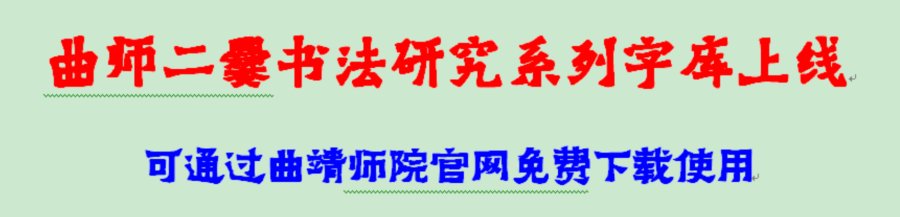
6月10日下午,由我校二爨书法研究所研发的“曲师大爨建国字库”上线,《爨体书法字库》首发,这是我校推进爨文化传承创新,继2017年“曲师二爨培生字库”上线之后,对“南碑瑰宝”爨龙颜碑和爨宝子碑进行数字化研发的又一重要成果。可通过曲靖师范学院官方网站下方快速链接免费下载“曲师二爨字库”,实现资源共享。
据悉,本次所推出的“曲师大爨建国字库”以“爨龙颜碑”为基础,在保持原碑风格特征的基础上,对原碑1239字(碑阳、碑阴)进行提炼和转化,以GB2312简体字库及GBK繁简字库为标准,对字形笔画的所有书写特点,造型元素反复揣摩,历经8万余字次的调整修正,推出“曲师大爨建国字库(简体)”“曲师大爨建国字库(繁简)”、“曲师大爨建国字库(繁体)”三个版本。《爨体书法字库》以“爨宝子碑”为基础,全部按照新华字典的编排体例进行编撰和书写,归类整理了所收集“爨宝子碑”各个时期的拓片版本,完成了石碑中407个字的书写,并进行了拓展。
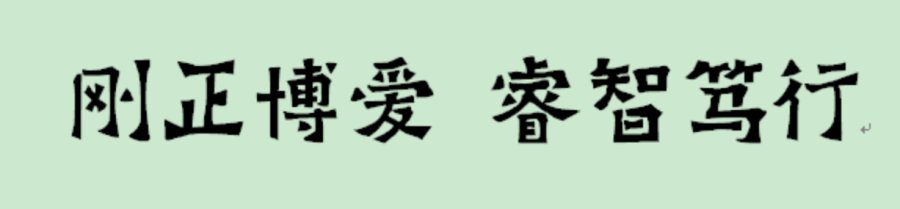
用“曲师大爨建国字库”书写的我校校训
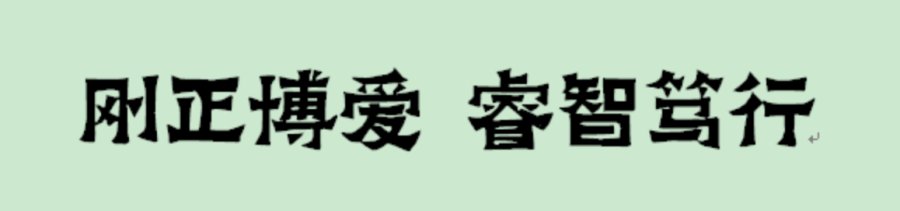
用“曲师二爨培生字库”书写的我校校训